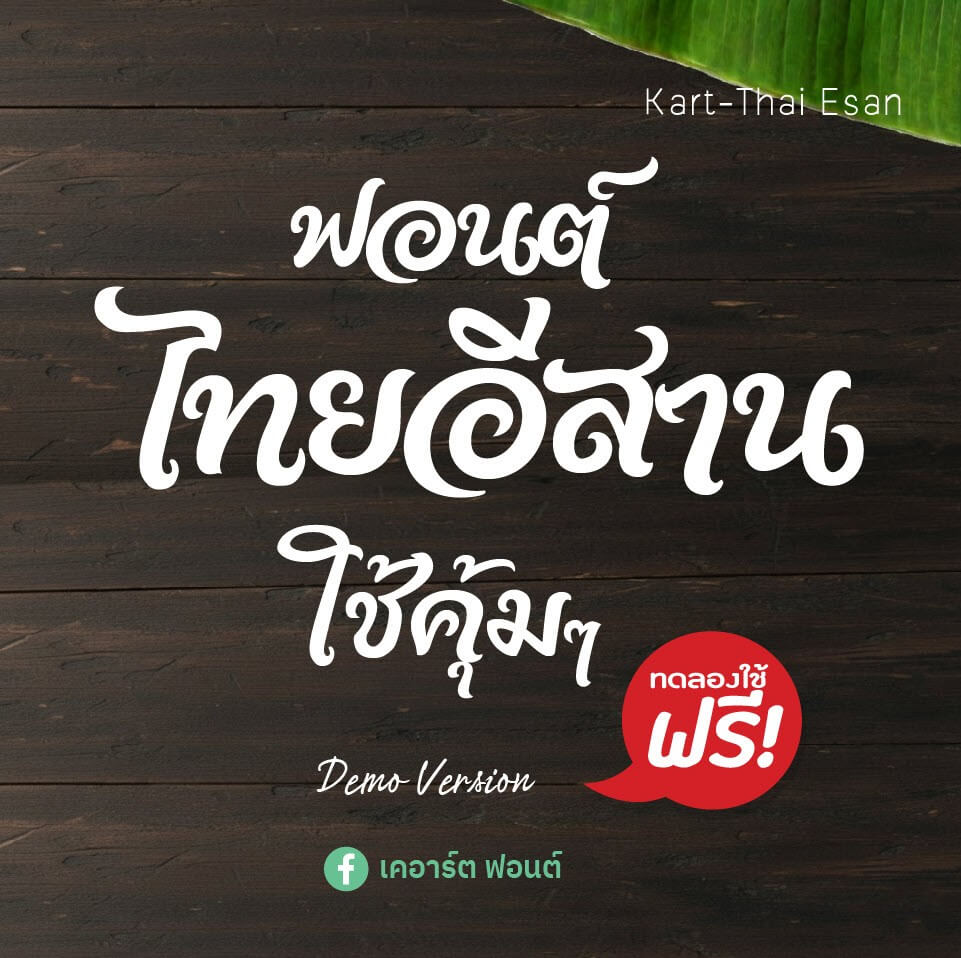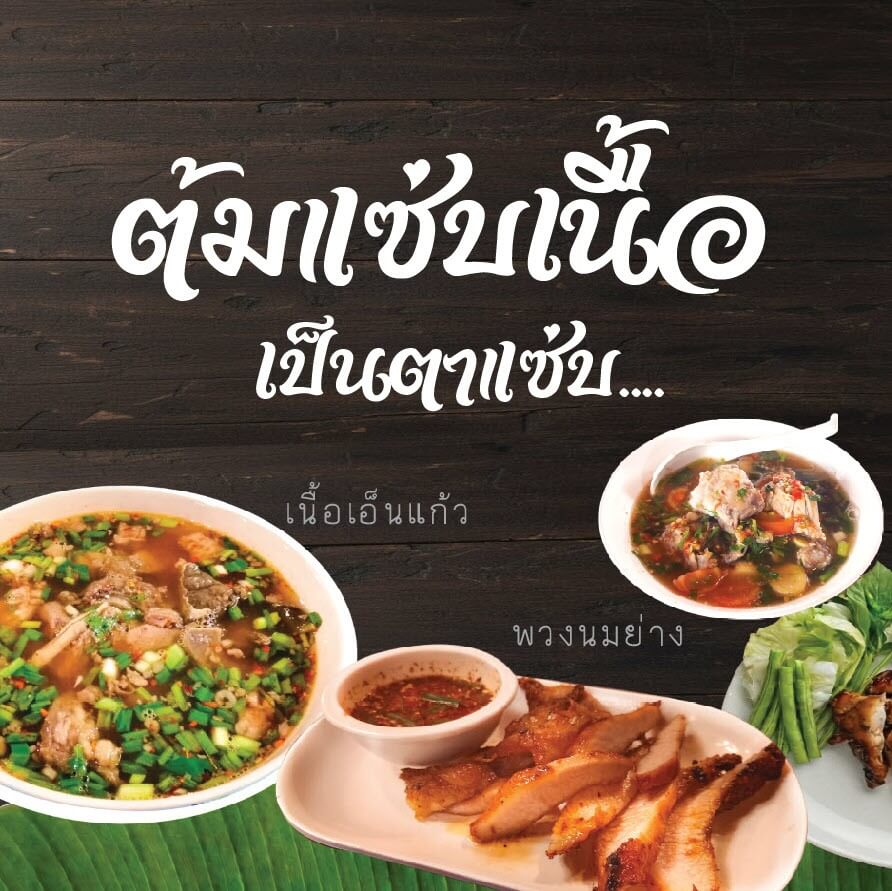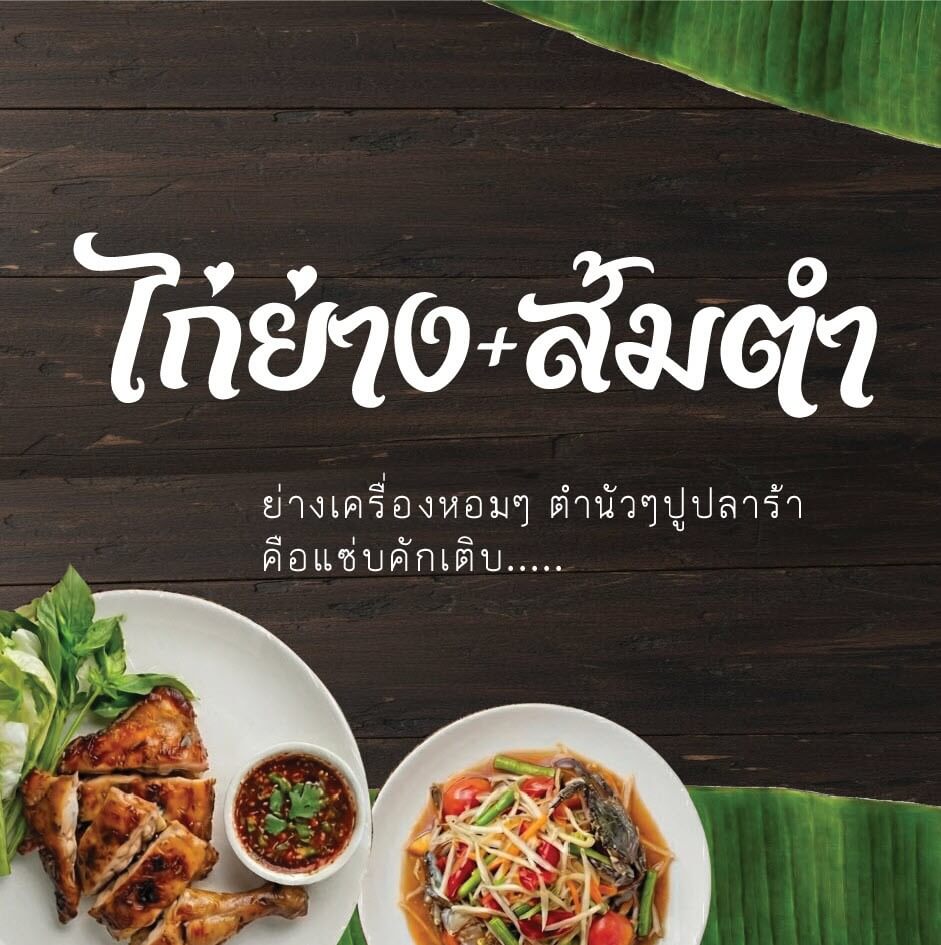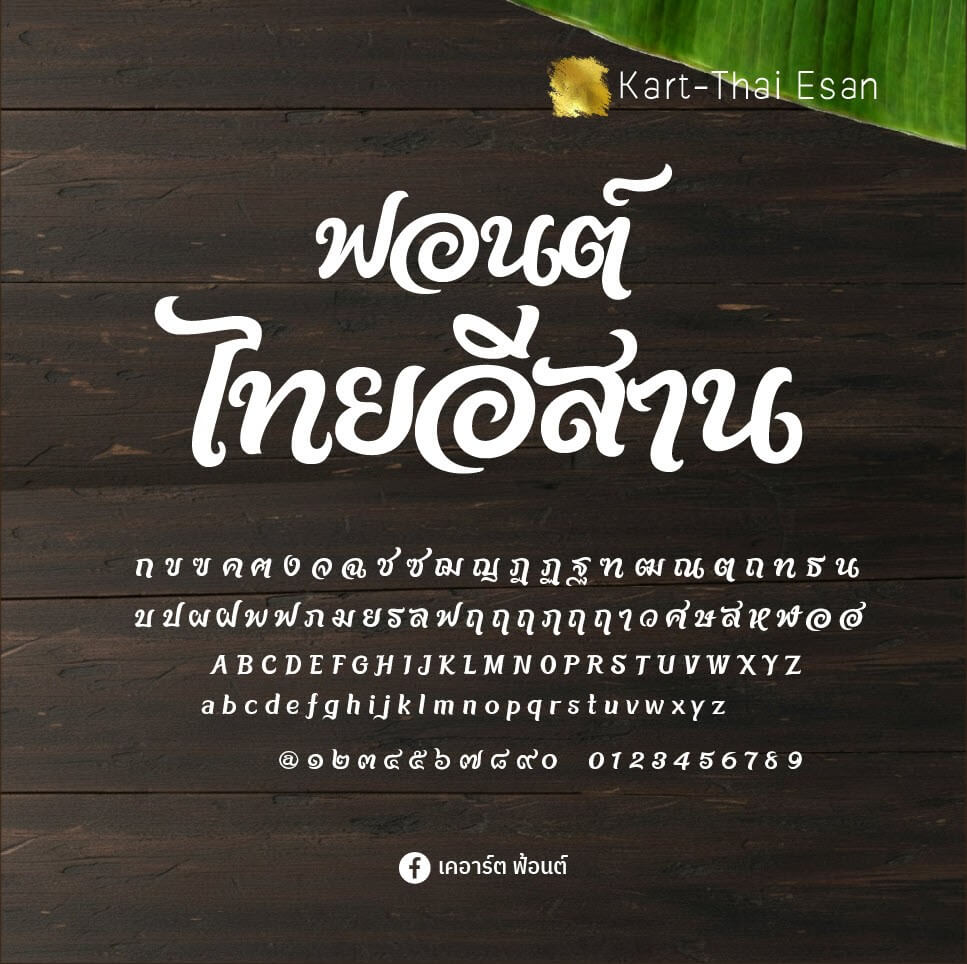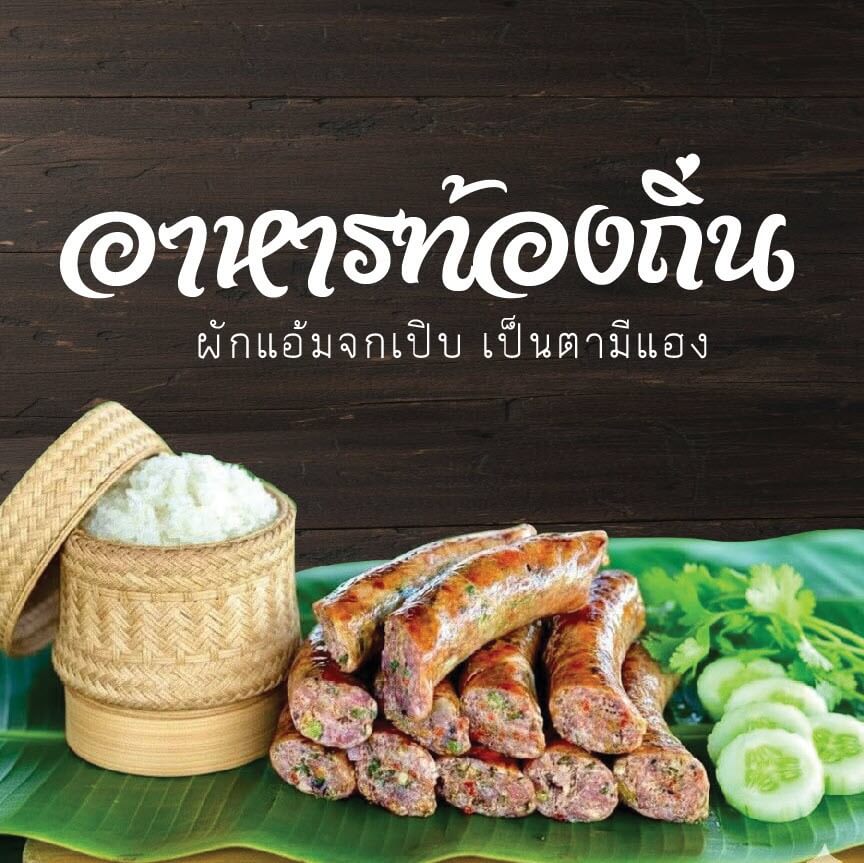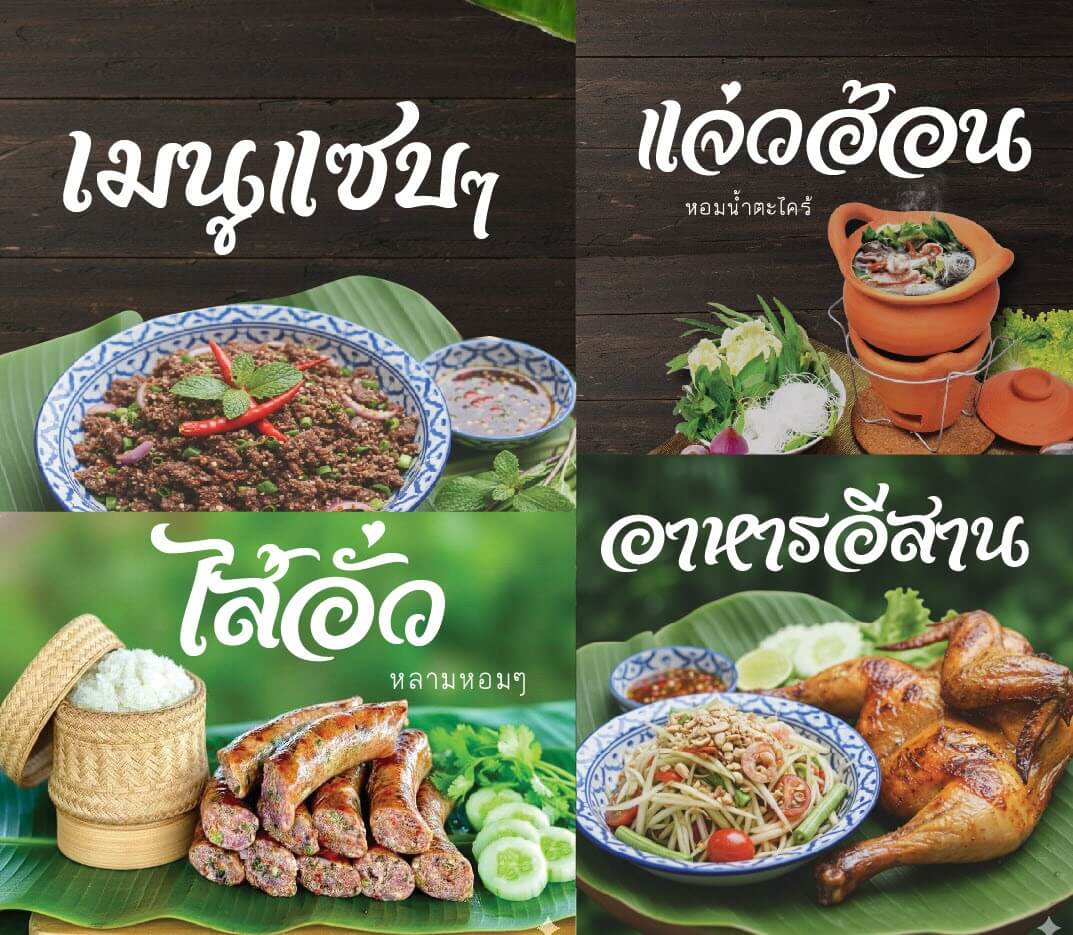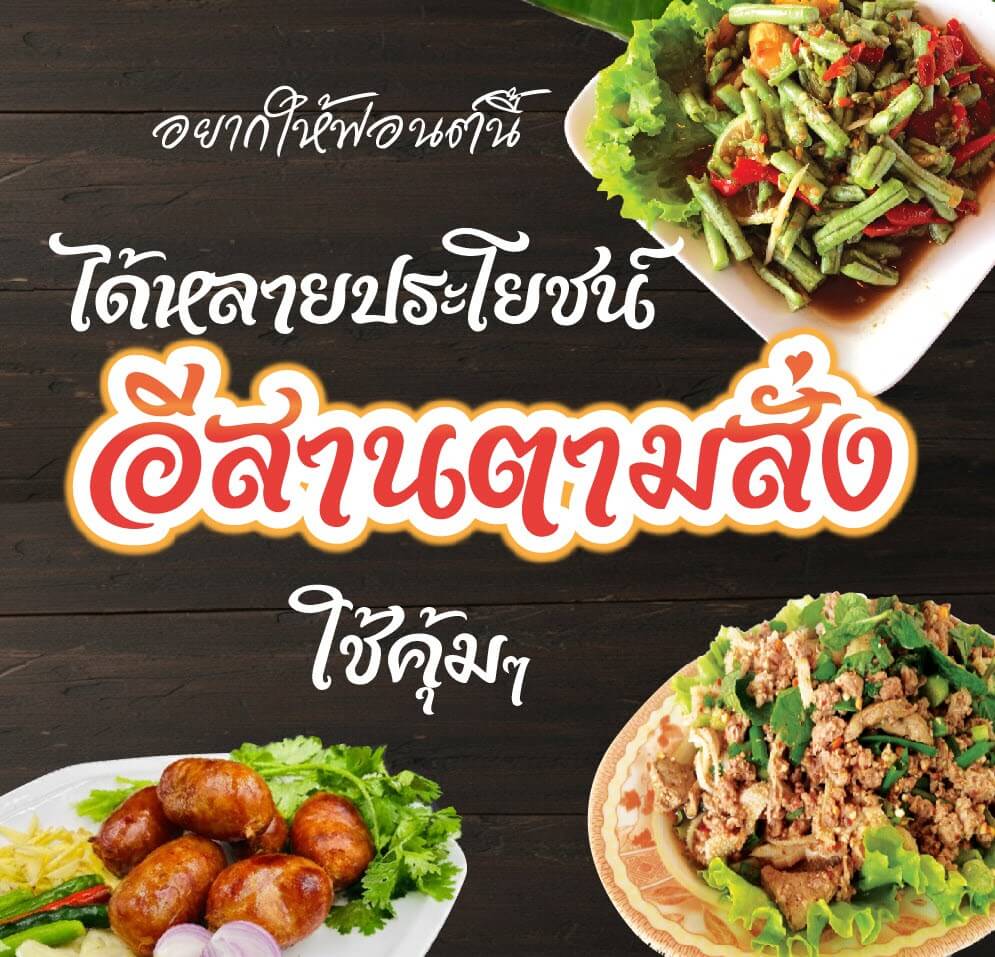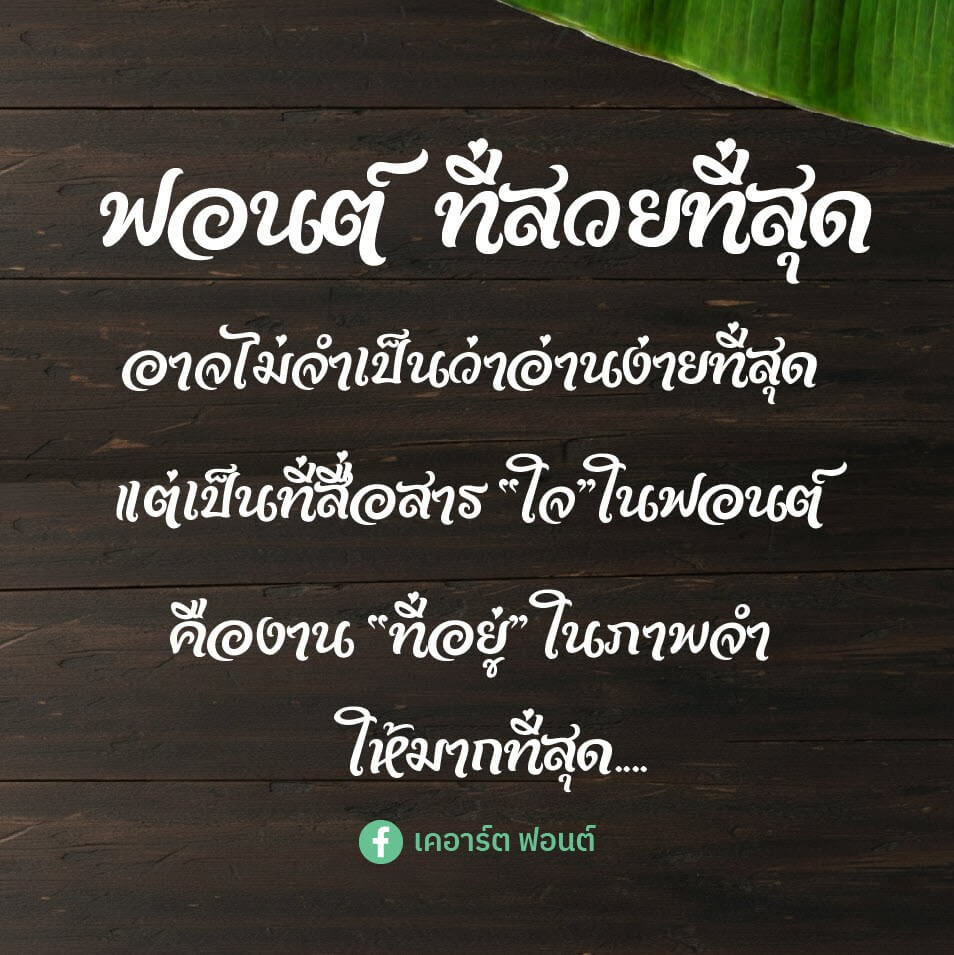
ฟอนต์ เคอาร์ต ไทยอีสาน (Kart-Thai Esan) – เป็นฟอนต์ที่เขียนไว้เน้นใช้คุ้มๆ กับทุกงานออกแบบป้าย+โลโก้ ฟอนต์นี้เป็นฟอนต์ตัวอย่างครับ
เคอาร์ต ไทยอีสาน (Kart-Thai Esan)